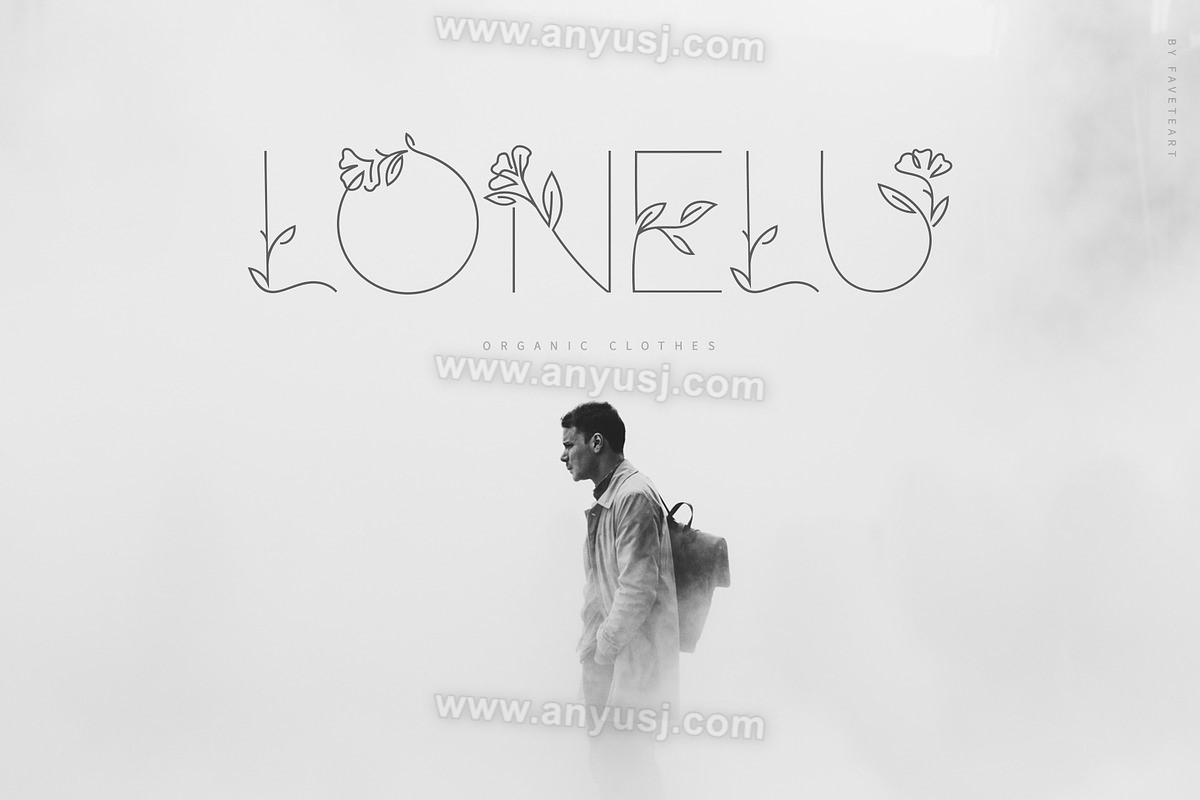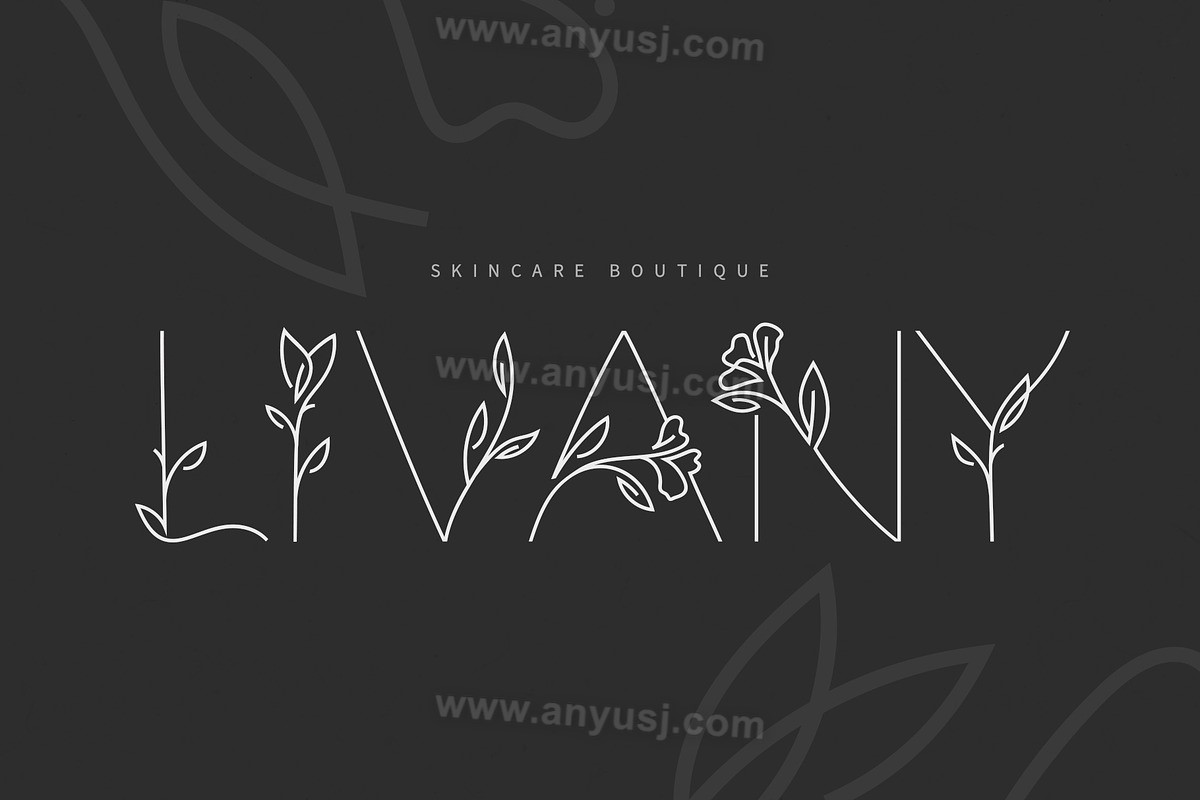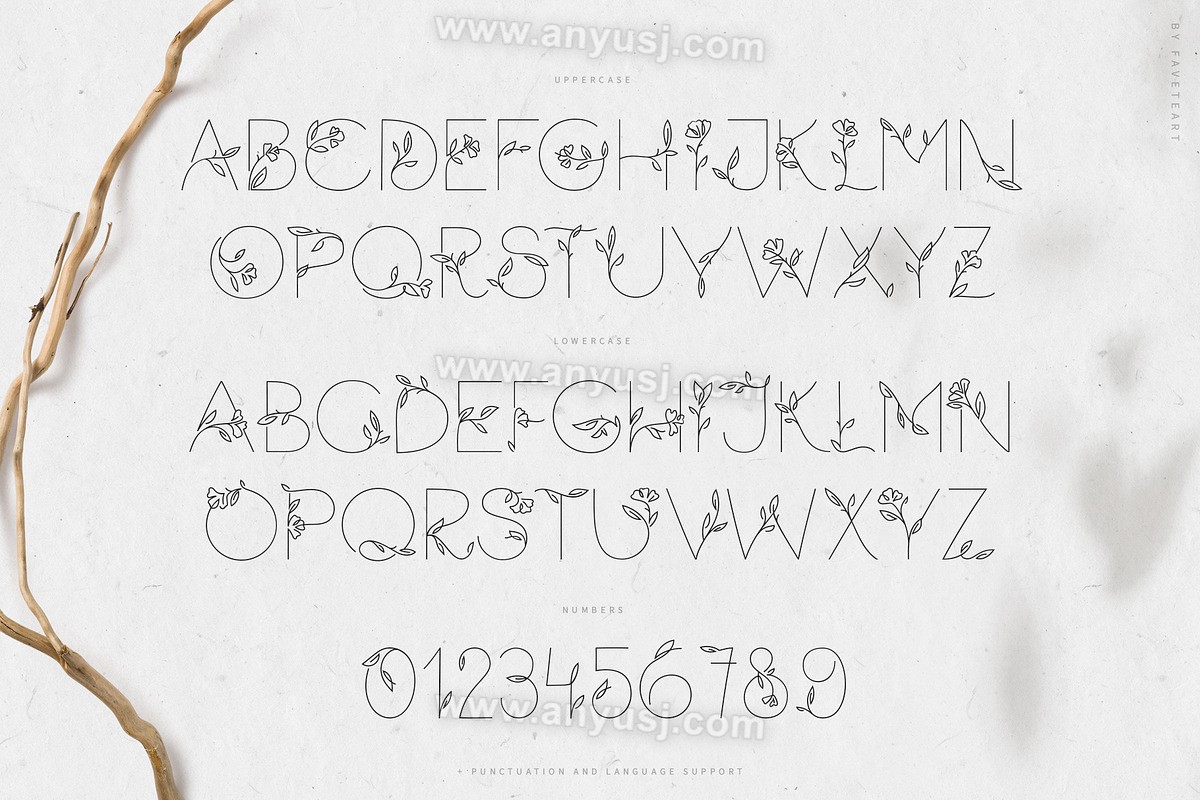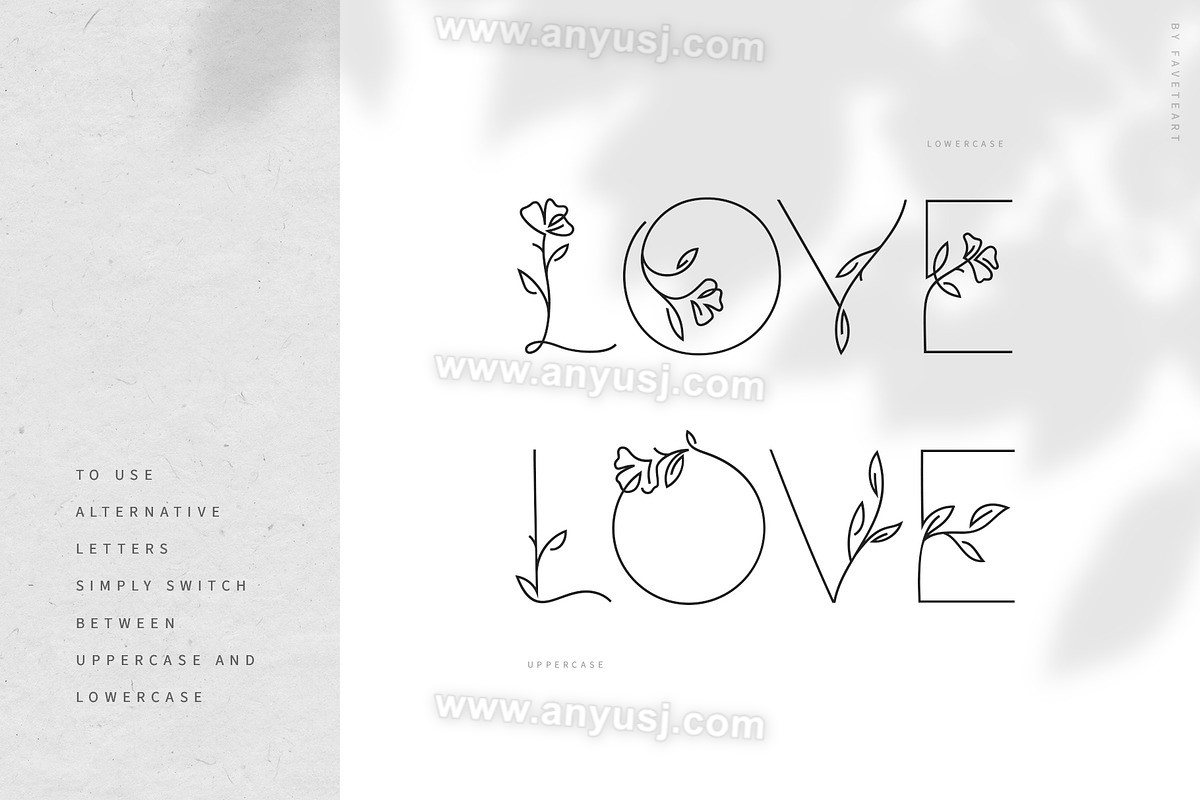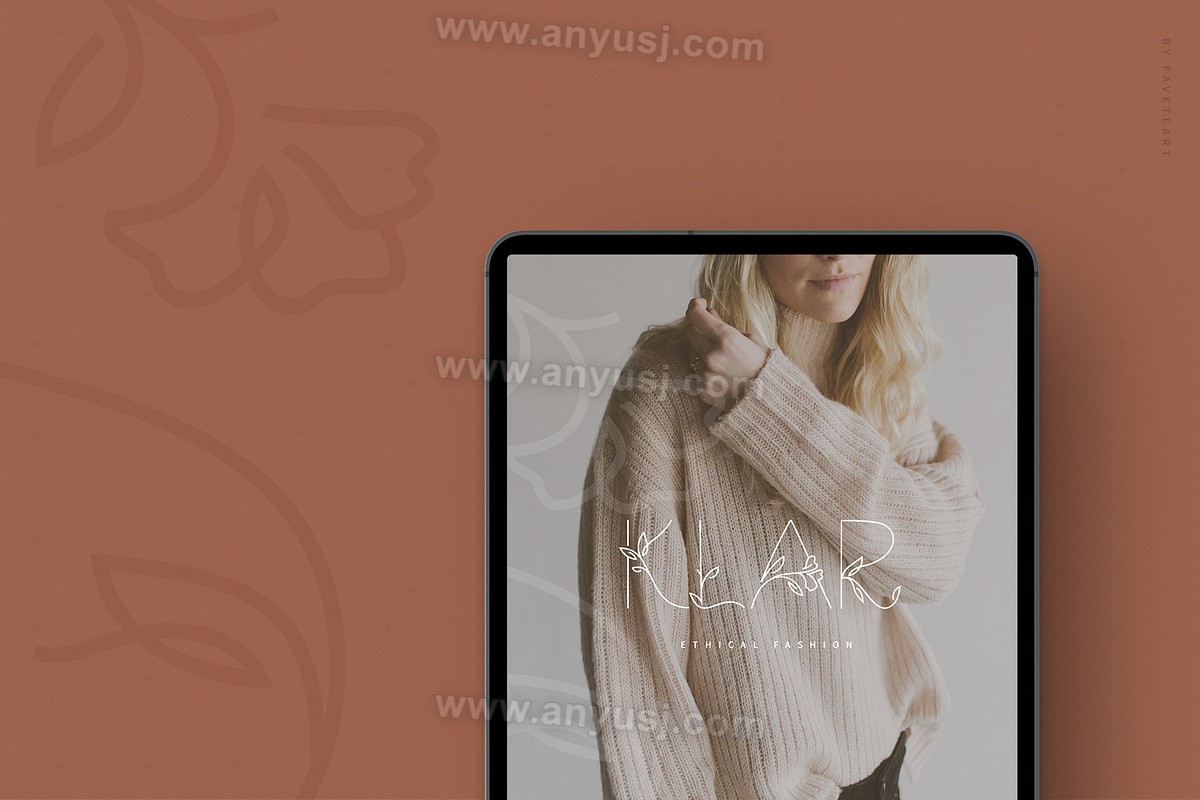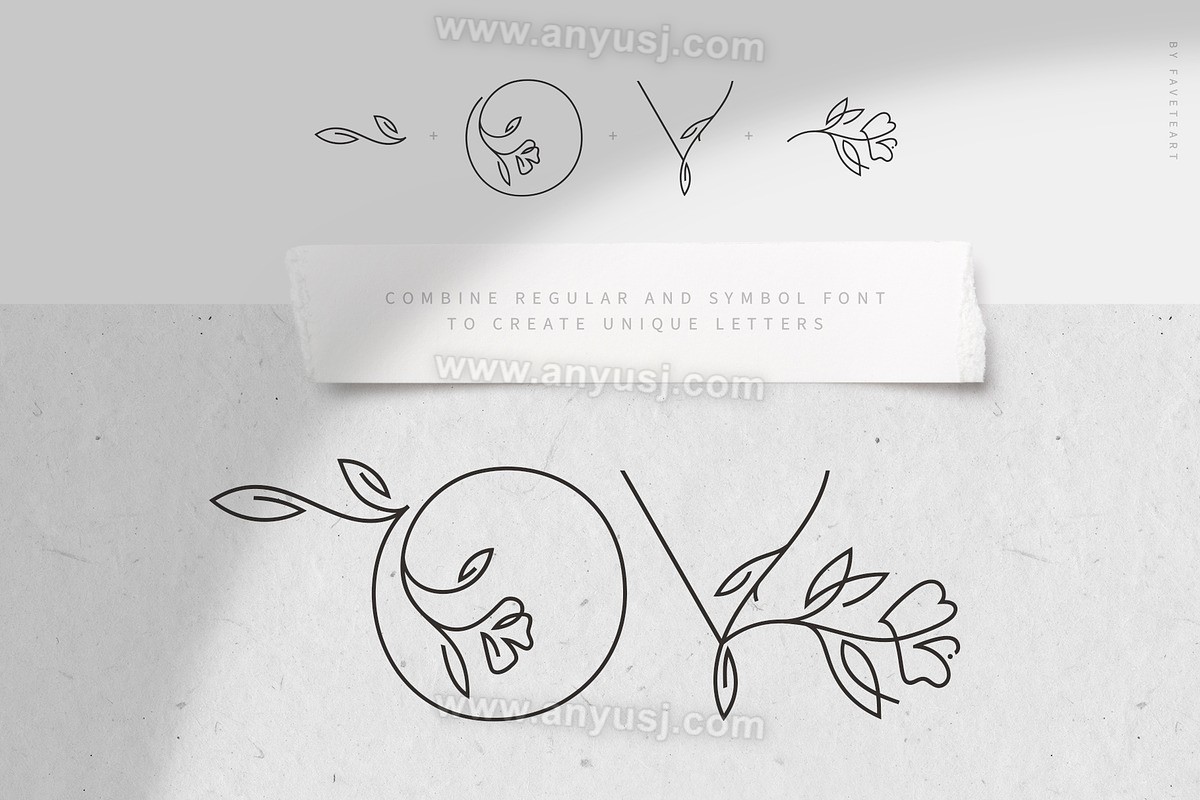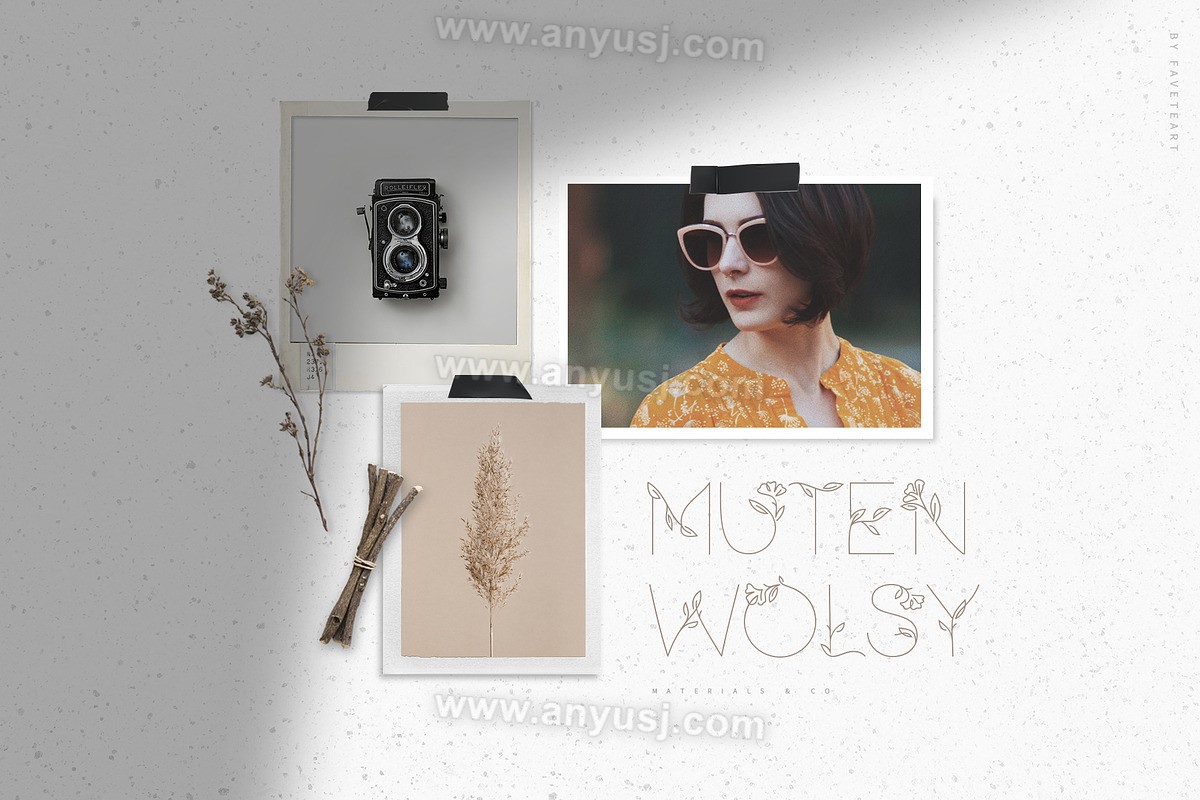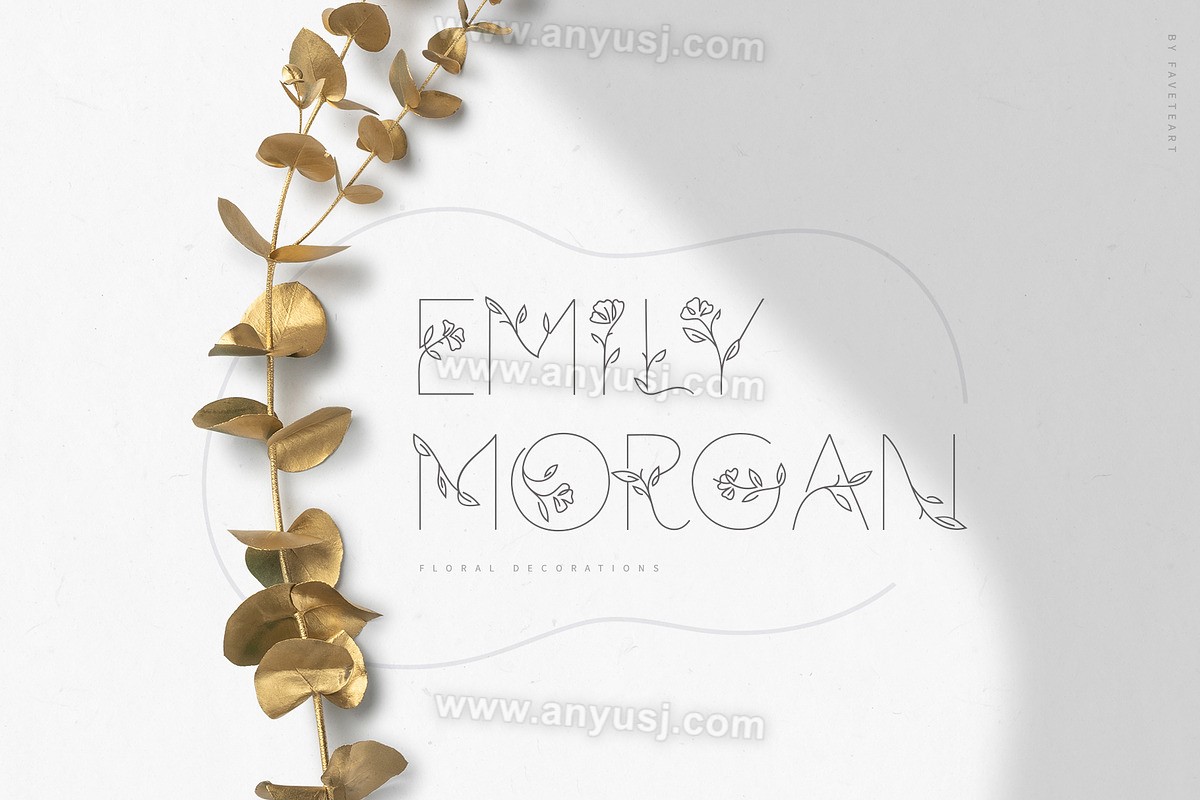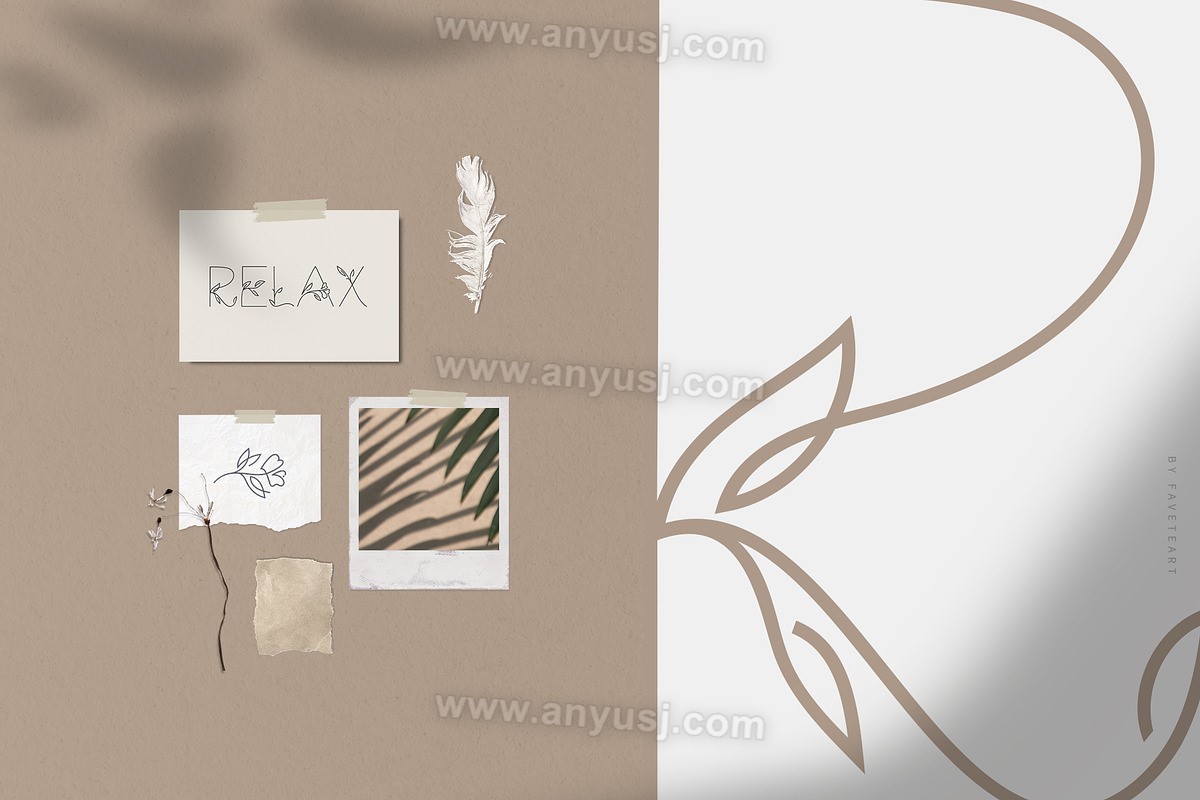
现代优雅干净化妆品护肤品花卉logo徽标标题排版装饰西文英文字体Florium – floral logo font
FLORIUM MODERN 徽标字体
我非常高兴地向大家介绍我的新字体 Florium。Florium 字体干净、简约、优雅,有两组字母,附有 62 幅漂亮的线条插图。
这种字体和符号将非常适合徽标、品牌、产品包装、海报、报价、社交媒体以及您需要引起标志或名称注意的所有设计。
- Florium 字体 – 优雅、干净、简约的大写字体,带有两组字母、数字、标点符号和 OTF 格式的语言支持。获得自定义感觉非常容易 – 只需在键入时在小写和大写之间切换,您就会得到不同的字母。
- 62 幅插图 – 精心制作的线条符号将帮助您创建自定义徽标和品牌元素。您将获得字体 – Florium_Symbols – 以及矢量格式(AI、EPS)和具有透明背景的单独 PNG 文件的插图。因此,您可以选择更易于使用的方法。
Florium 支持大多数常见的拉丁语,仅举几例 – 阿尔巴尼亚语、波斯尼亚语、加泰罗尼亚语、克罗地亚语、捷克语、丹麦语、荷兰语、英语、世界语、爱沙尼亚语、菲律宾语、芬兰语、法语、德语、匈牙利语、印度尼西亚语、爱尔兰语、意大利语、拉脱维亚语、立陶宛语、挪威语、波兰语、葡萄牙语、罗马尼亚语、斯洛伐克语、斯洛文尼亚语、西班牙语、土耳其语